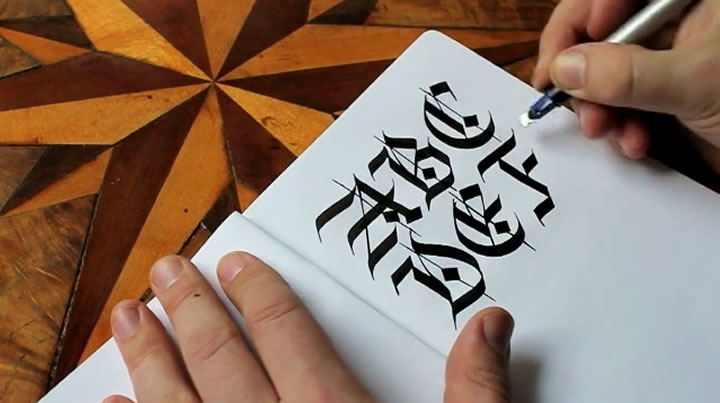
Sketchbook est une vidéo réalisée par Seb Lester qui nous montre son projet typographique sur la font Blackletter.
Blackletter a été utilisé à travers l’Europe à partir des années 1150 jusqu’à la fin du 17ème siècle. Une des préoccupations de Seb s’oriente vers un ensemble de capitales gothiques modernes et très lisibles. Les lettrines sont dans un style gothiques, tout en conservant la richesse et la beauté inhérente à cette ancienne catégorie de fonts.
Vous allez voir dans cette vidéo un live de la création du début de l’alphabet. Impressionnant de précision.